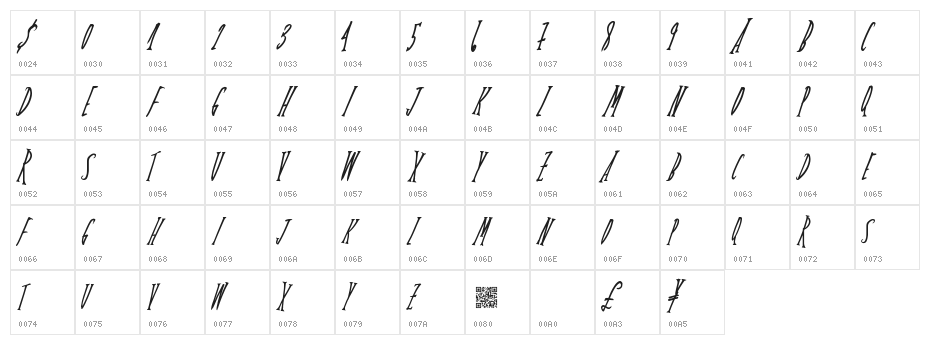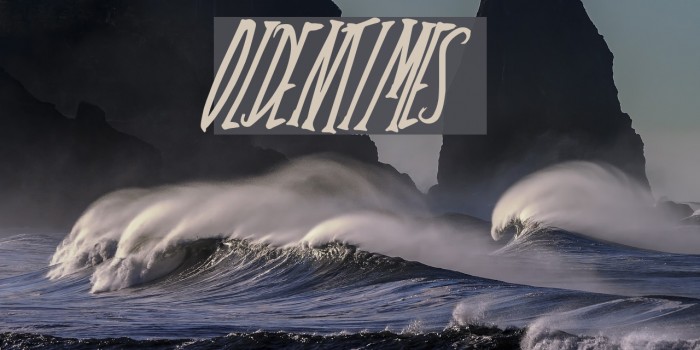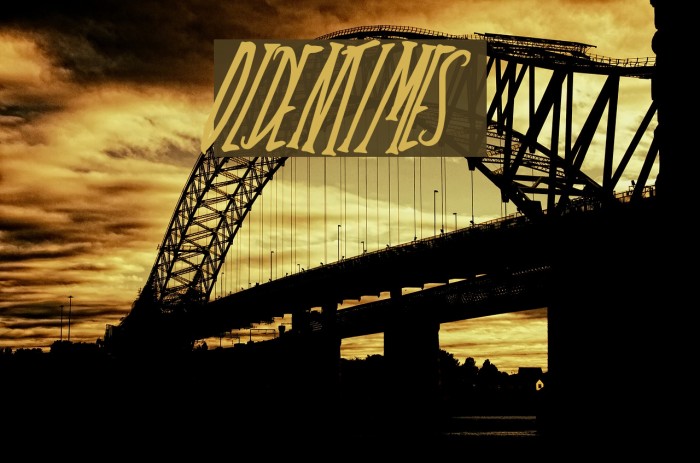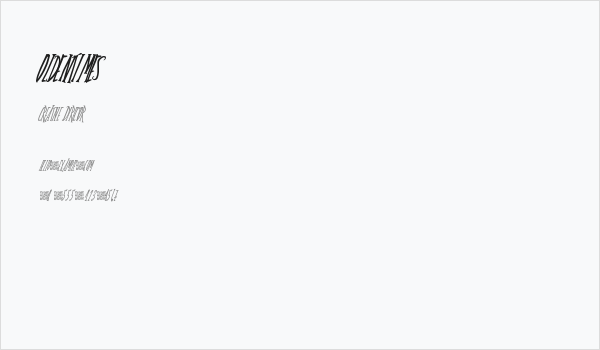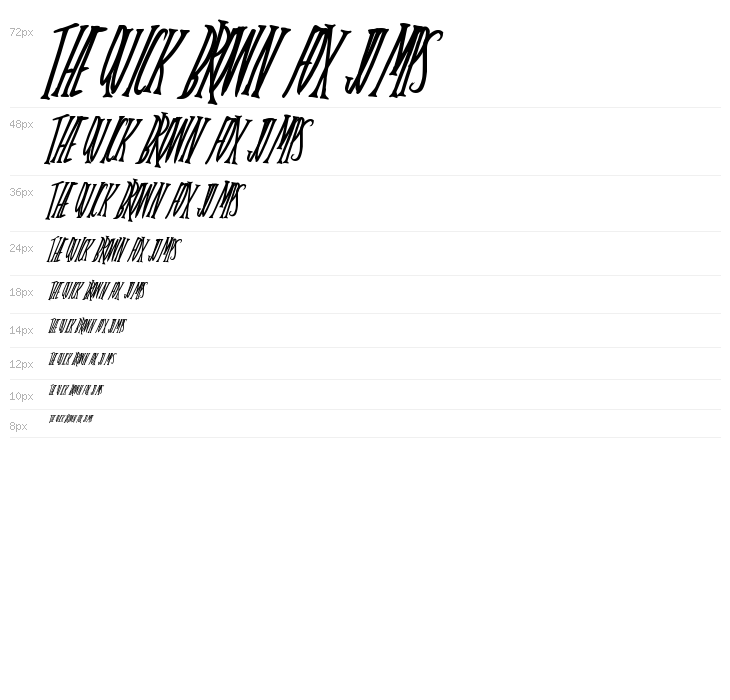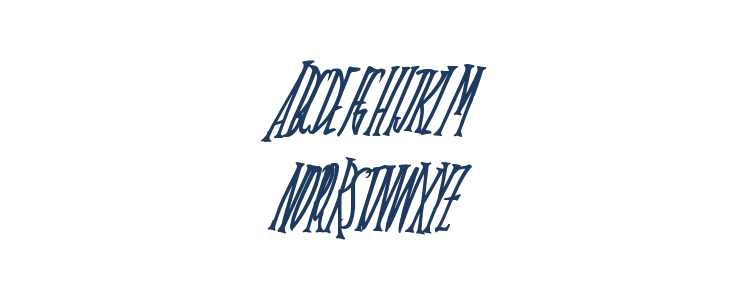
OldenTimes Font
✎ Calligraphic
| الفئات | Calligraphic |
| مائل | Yes |
| العرض | Condensed |
| مشاريع مقترحة | Ideal for creative projects such as posters, album covers, branding for artistic ventures, and any design requiring a bold, expressive typeface. |